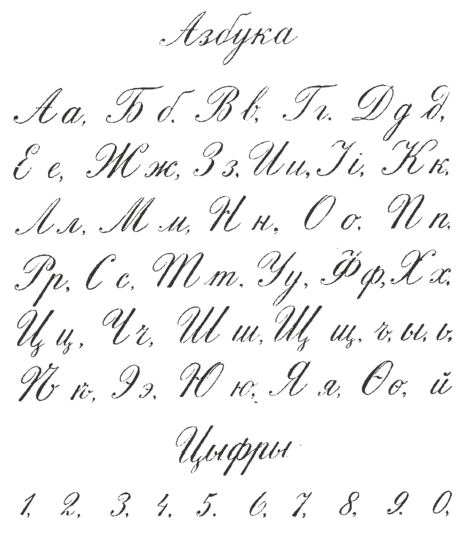
1. Определитесь, зачем вам это нужно
У желания улучшить почерк могут быть разные причины. И вам стоит найти вашу. Во‑первых, это заставит вас действовать более осознанно и повысит мотивацию. А во‑вторых, подскажет, на исправлении каких нюансов почерка нужно сосредоточиться.
Возможно, вы просто хотите писать разборчивее. Или чувствуете необходимость сделать почерк более «начальственным» — придать ему уверенность, чёткость, эффектность. А может, вами движет исключительно эстетическое чувство. Разберитесь с собой, это важно.
2. Оцените свой актуальный почерк
Возьмите лист бумаги и напишите на нём несколько предложений — так, чтобы они образовали два‑три абзаца. Не старайтесь выводить буквы «красиво», пишите естественно — так, как делаете это всегда.
Когда закончите, положите лист перед собой и проанализируйте видимые недостатки почерка. Делайте это не в целом («как курица лапой!»), а стараясь выделить конкретные моменты.
- Форма букв. Возможно, они слишком узкие и угловатые? Или наоборот, излишне округлые, с затейливыми петлями? Может, они дублируют друг друга — например, «п» в вашем исполнении выглядит как «и»?
- Наклон. В классическом красивом почерке все буквы имеют одинаковый лёгкий наклон вправо.
- Высота букв. В идеале она должна быть одинаковой и такой, чтобы значки были читаемы. А как у вас?
- Написание букв. При анализе может оказаться, что один и тот же элемент вы изображаете по‑разному. Классический пример — разница в начертании буквы «т»: иногда используется её печатный вариант, а иногда — письменный.
- Интервал между буквами. Он тоже должен быть равномерным.
- Расположение букв на горизонтали. Они не должны прыгать или уходить вверх‑вниз к концу строки.
- Нажим. Давление пера на бумагу должно быть равномерным на всём протяжении текста. Но часто бывает так, что в одном месте мы слишком давим на ручку, а в другом, напротив, она будто соскальзывает с бумаги, из‑за чего текст выглядит неряшливым и плохо читаемым.
Для наглядности можно подчеркнуть или обвести самые «выдающиеся» участки текста контрастным цветом. Это поможет вам сконцентрировать внимание на тех недостатках, от которых вы хотите избавиться. Например, если вы отметите, что буква «ж» выходит у вас скомканной, сжимающейся в конце, в будущем вы постараетесь сделать её более равномерной.
3. Найдите источник вдохновения
Красота — понятие относительное, и «красивые» (на ваш взгляд) почерки могут быть совершенно разными. Поищите пример того, который вам нравится.
Возможно, это будут просто идеально ровные «школьные» строчки:
900igr.netИли изящные каллиграфические:
Youtube‑канал AlphabetManА может, вы жаждете оригинальности и вам больше по душе почерк с наклоном влево? По возможности, распечатайте найденные примеры и разложите их там, где они будут попадаться вам на глаза. Например, повесьте на дверь холодильника. Прикрепите в виде стикера на монитор. Или над рабочим столом.
4. Делайте зарядку для рук
За почерк отвечает то, что физиологи называют мелкой моторикой — совокупность скоординированных действий кисти и пальцев рук. Если вы стараетесь, а с почерком беда, то, возможно, проблема как раз в моторике. Выход один: тренировать руки.
Среди самых эффективных и одновременно простых способов — воздушное письмо. Возьмите ручку или карандаш, согните руку в локте (на угол около 70–80 градусов) и начинайте писать воображаемые слова прямо в воздухе. Делайте буквы крупными — в этом случае при выписывании будут задействованы не только кисть и пальцы, но и вся конечность от плеча, включая запястье и предплечье. Это важно: вы меньше утомляетесь, если пишете всей рукой, а это позволит сохранять почерк более чётким и ровным.
Такие упражнения стоит проводить регулярно. Например, тратить на них по 3–5 минут утром, днём и вечером.
5. Убедитесь, что вы правильно держите ручку или карандаш
YouTube‑канал «Хочу всё знать»Пишущая принадлежность должна лежать на левой стороне среднего пальца правой руки (если вы левша — на правой стороне среднего пальца левой руки). Кончик указательного пальца придерживает ручку или карандаш сверху. Большой поддерживает слева (для левшей — справа). Когда вы пишете, рука должна опираться на верхний сустав согнутого мизинца.
Все три пальца, удерживающие ручку или карандаш, чуть скруглены и не сжимают канцелярскую принадлежность слишком сильно.
Чтобы проверить правильность хватки, поднимите указательный палец. Ручка (карандаш) не должна упасть.
6. Подберите качественные канцелярские принадлежности
Чтобы почерк получился приближённым к идеалу, вы должны получать удовольствие от письма. Поэтому ищите принадлежности, которые не царапают бумагу, а оставляют на ней мягкий отчётливый след. Найдите толщину линии, которая вам нравится. Поэкспериментируйте с цветами.
К качеству бумаги тоже стоит подойти пристрастно. Выбирайте офисные листы плотностью около 90 грамм на квадратный метр с умеренно гладкой, но не глянцевой поверхностью.